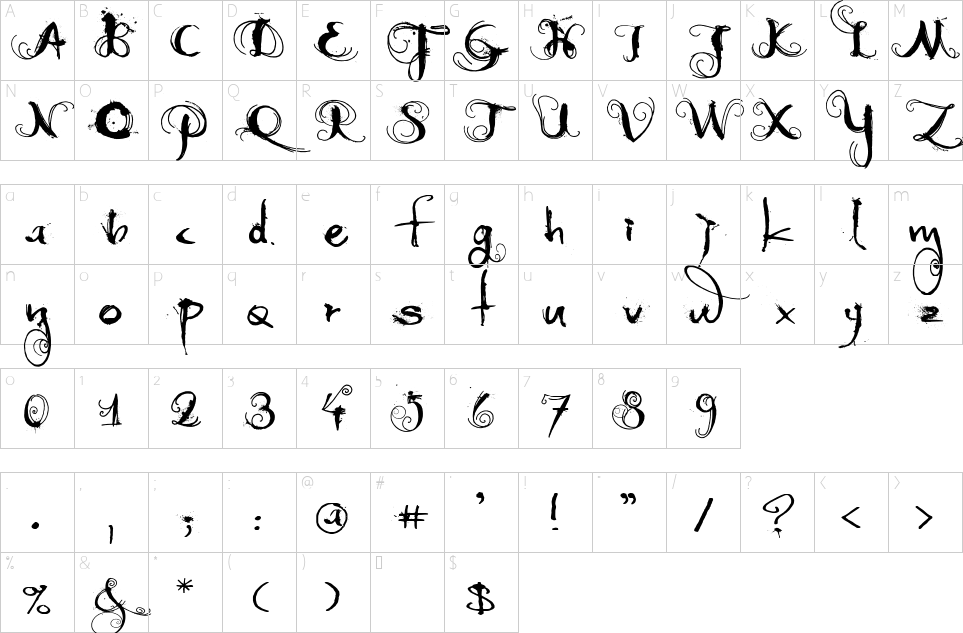
A fonte Moonlight Shadow é um charme que encanta os olhos com sua delicadeza e elegância. Inspirada no brilho misterioso do luar, essa fonte macia e suave é perfeita para textos que buscavam um toque delicado e distinto. Desenvolvida por Hanoded, a Moonlight Shadow é um presente para todos os criativos que desejam adicionar um toque único e romântico aos seus projetos digitais. Com seu design sofisticado e seu uso em diversos dispositivos, desde computadores Windows até Mac, Moonlight Shadow se torna uma opção valiosa para aqueles que buscam um recurso gráfico diferenciado e gratuito. Mais de 19.731 downloads confirmam a qualidade e a popularidade dessa fonte, tornando-a uma escolha atraente para designers e criadores de conteúdo em busca de uma solução elegante e moderna.